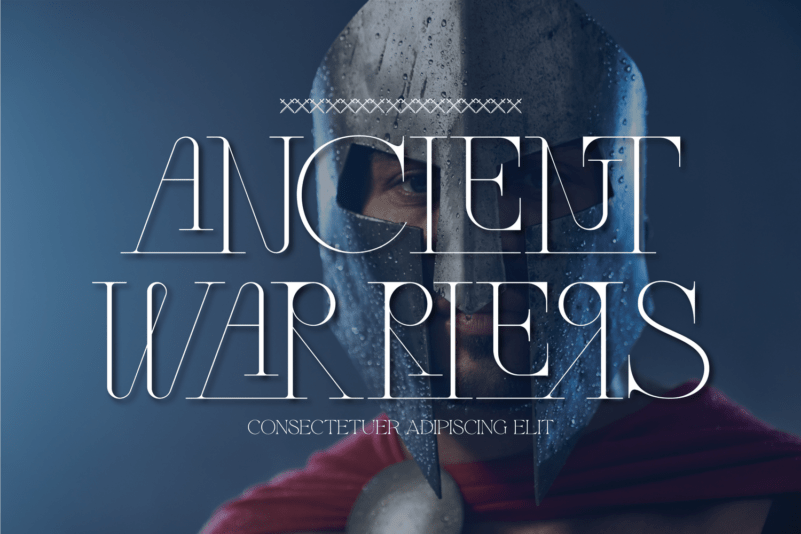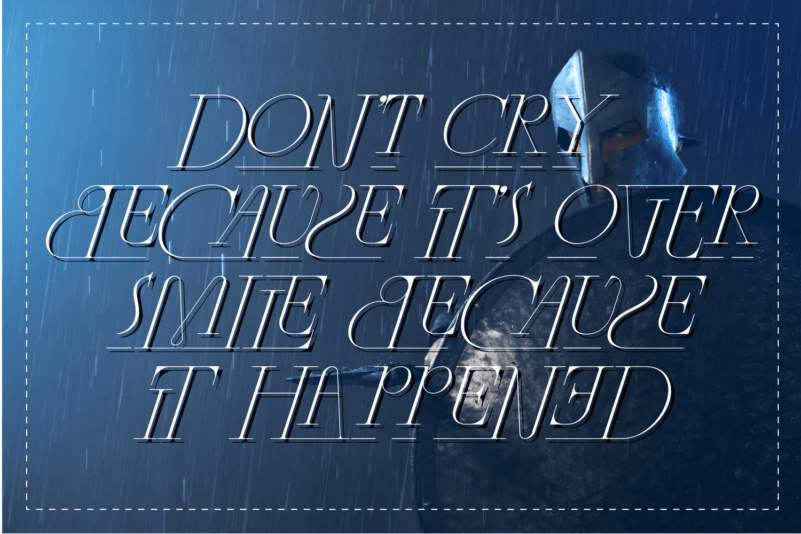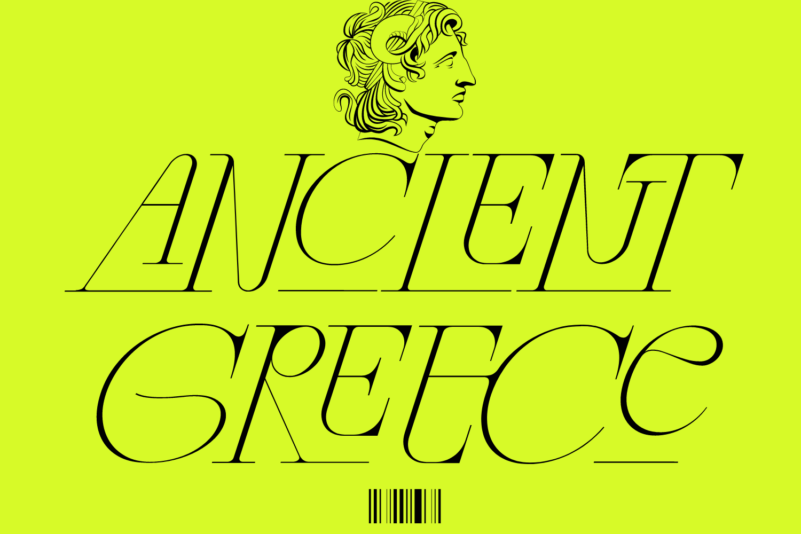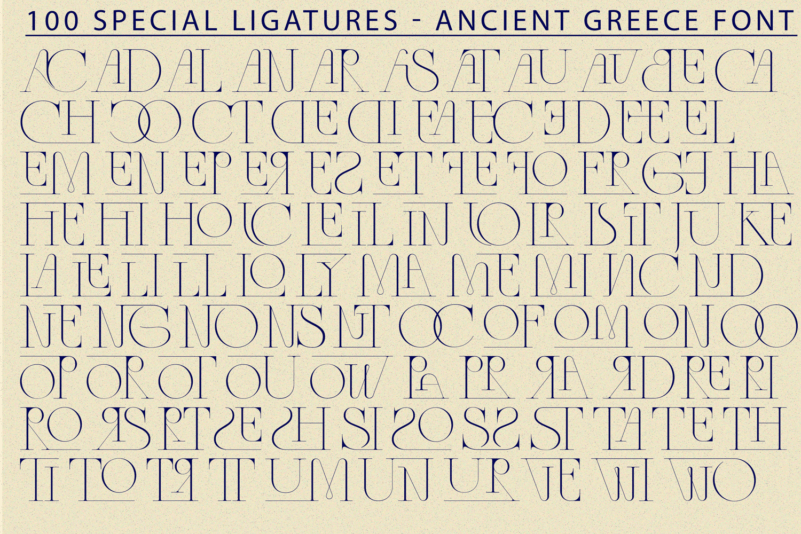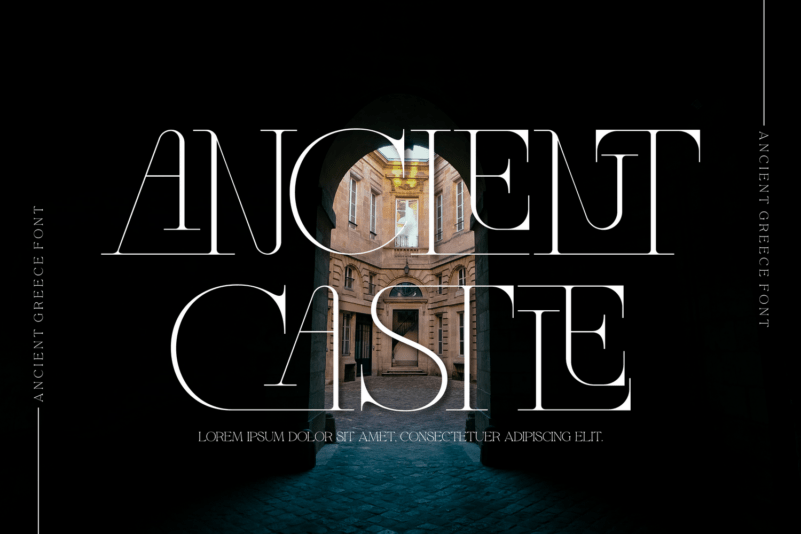
Ancient Greece优雅衬线英文字体
一款具有古希腊风格的英文字体,采用优雅的衬线设计,具有独特的风格化交替和连字符,展现出复古和时尚、怀旧和超级优雅、现代和艺术装饰的特点。包括细码到超粗码及斜体共4种风格,此字体适用于标识、报价、海报、品牌宣传、网站标题、新闻简报等多种场合。它包含超过100个连接字和一些别致的备用字母,可以结合使用,创造出多样的外观效果。